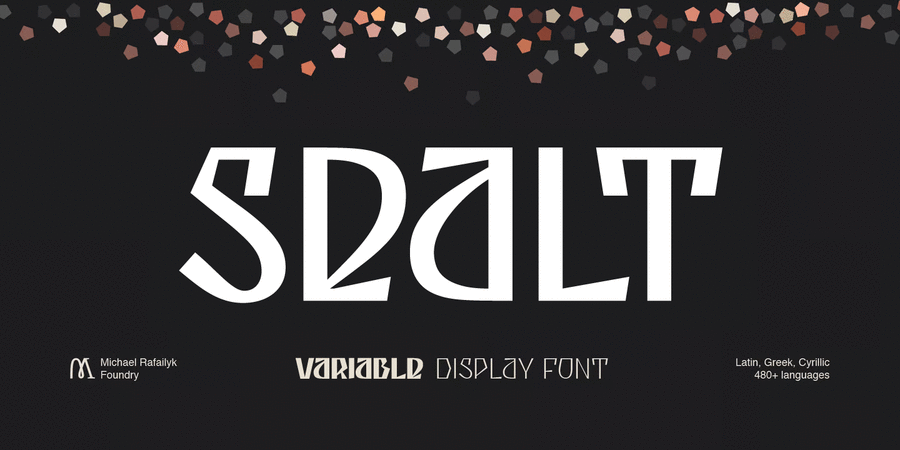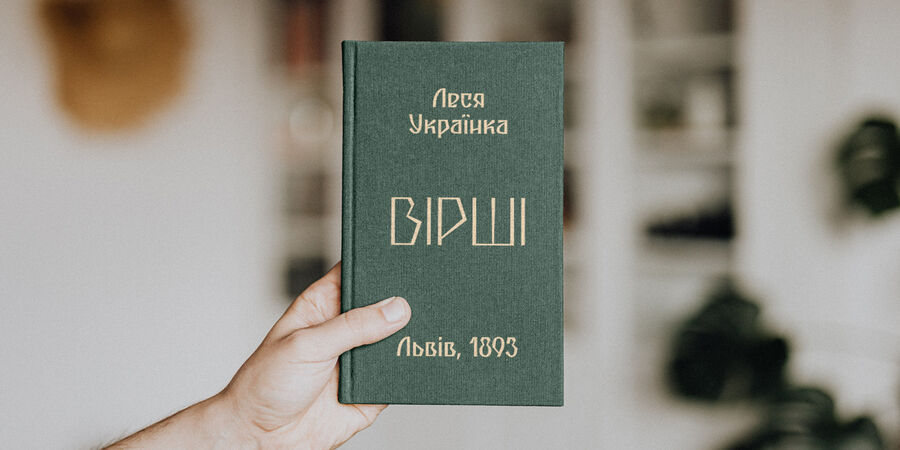
Шрифтову гарнітуру Sealt присвячено найдавнішій солеварні у східній Європі, заснованій у 1390 році у місті Дрогобич. Sealt у перекладі зі староанглійської означає сіль, тож більшість літер виглядають грубо та гостро, як кристали солі, і ніби вирізані зі скелі.
Variable font: Sealt VF має варіативну вісь Weight яка включає сотні стилів від Light (300) до Bold (700), тож вільно обирайте найточніший стиль за допомогою повзунка у графічному редакторі чи за допомогою CSS на веб сторінці.
Localized Forms: 47 символів автоматично змінюють свій вигляд для наступних мов – азербайджанська, болгарська, каталонська, голландська, німецька, казахська, молдавська, польська, румунська, татарська, турецька.
Glyph Composition/Decomposition (Діакритичні знаки): Повний набір латинських та базовий набір в'єтнамських літер із діакритичними знаками (561 літера).
Ordinals: adehnorst.
Superscript, Subscript, Numerator, Denominator: 0123456789.
Fractions: ¼½¾⅐⅑⅒⅓⅔⅕⅖⅗⅘⅙⅚⅛⅜⅝⅞⅟. Будь-які інші комбінації чисел дробів (навіть набрані через slash) також будуть скомпоновані на льоту з заміною чисел на Numerator + Denominator, а символу slash – на fraction.
Slashed Zero: усі цифри 0, в тому числі Lining, Superscript, Subscript, Numerator, Denominator, та Fractions, замінюються на нуль зі слешем.
Contextual Alternates: ΆΈΉΊΌΎΏ. Грецькі великі літери у режимі All Caps втрачають акцент tonos (але залишають акцент dieresis). Увімкнено за замовчуванням.
Standard Ligatures: OO TT tt fi. Увімкнено за замовчуванням.
Писемності: Латиниця, Грецька, Кирилиця.
Шрифт розробив Михайло Рафайлик у 2021-2023 році.
Асоціації з сімейством шрифтів SealtОсобистість і характер гарнітури:
твердий, гордий, вільний, сильний, героїчний, темпераментний, мотивуючий, активний, амбітний, залізний, релігійний, історичний, екологічний, добротний, сміливий, самобутній, характерний, оригінальний, різкий, гострий, етнічний, натуральний, традиційний, колоритний, артистичний, художній, динамічний, ностальгічний, ремісничий, виразний, консервативний, племінний, артізанальний, природний, рукотворний, войовничий, хоробрий, бравий, важкий, чіткий, жорсткий, сталевий, незвичайний, авторитетний, переконливий, монументальний, архітектурний, впевнений, яскравий, помітний, експериментальний, лицарський, благородний, красивий, майстерний, легендарний, аристократичний, старовинний, пивний, пафосний, освічений, якісний, дорогоцінний, унікальний, дзвінкий, біблійний, християнський, церковний, сакральний, екстравагантний, крафтовий, казковий, чарівний, химерний, вигадливий, епічний, середньовічний, музичний, творчий, фантастичний, старомодний, мужній, кінематографічний, ефектний, культурний, естетичний, урочистий, видовищний, кам'яний, цікавий, колючий, дивний, серйозний, карбований, важливий, вольний, бунтівний, суворий, грубий, плоскінний, сірмяжний, сільський, рубаний, ламаний, кристальний, холодний, крижаний, зухвалий, скляний, тонкий, легкий, сріблястий, срібний, сухий, крихкий